използване пишещи машини шрифт, имена, историческа информация
Старомодни шрифтове, които имитират пишеща машина, днес широко използвани в уеб дизайна. Те дават текста особен чар и елегантност, но са приложими, разбира се, не във всички случаи.
историческа информация
Преди появата на компютърни системи за писане, използвани пишещи машини. Те са създадени предимно за пренаписване на ценни книжа и ръкописи. Пишеща машина на шрифта не е само груба и малко неясна. Когато един от първите изобретатели на това устройство, М. Алис, представени тяхното потомство, много не го харесвам, защото героите са Etalon гладки като от принтера. Това създаде известни затруднения с набора от документи, необходими, за да ги подлагат на цензура. Останалата част от изобретателите са взети под внимание тази грешка, и пишещата машина на шрифта е станал това, което ние я познаваме днес.
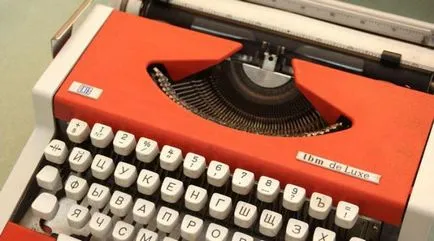
В пишещи машини използват т.нар едноразряден шрифт, който се характеризира с еднакви символи широки. Смята се, че тя е по-неразбираем от един пропорционален на шрифта, който се използва в съвременната печат. Но днес тя се намира в програмирането, когато пишете код, този шрифт за писане на сценарии. Между другото, регистрационни номера, също са написани на Непропорционални шрифтове.
За да спестите място и намаляване на размера на устройството е често отделят много от ключовете. Така например, номера заменени heteronymous букви, тирета и тирета, са същите като цитати.
използването на
По-голямата част на ХХ век, всички официални държавни документи са написани на пишеща машина, издателят се изисква също да донесе отпечатания текст, тъй като това значително улеснява работата на Наборчици.
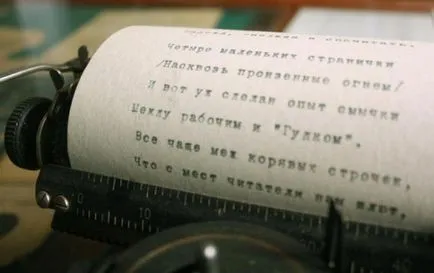
В средата на ХХ век, с появата на персоналните компютри, пишещи машини няма. Но пишеща машина шрифта е все още активно се използва от дизайнерите. Тя изглежда страхотно в много стилове, дава реколта ефекти. Впечатлението на работата на човека, а не прави бездушна машина.
Какво е името на пишеща машина на шрифта?
В момента има повече от 15 разновидности на тях за Photoshop. Всеки шрифт пишеща машина за "Photoshop" или имитира стила на конкретно устройство или пише в различни публикации (вестници, печат). Много стилове са на разположение и в двете на кирилица и латиница. Най-подобен шрифт изглежда B52 с голямо разстояние между знаците и ефекта на триене. Има и други шрифтове, например:
- DS Moster има доста интересен ефект, когато някои печатни са символи, които по-дебели. И писмата не са подредени точно в съответствие и "танц" прави текста много реалистичен.
- Underwood напълно копира стила на писане на едно и също име на машината.
- Хартинг и 1942. Доклад изглежда много износени, сякаш боята в машината започва да се изчерпи.
- Junkos пишещи машини силно стилизирани буквите в нея с различни размери и материал, много "мастилени петна".
- Пишеща машина, Тип наред и крал по-голям по-близо до компютъра или наборен, те са ясни, гладка и без малки петна.
- Стари вестници е подобно на стила на печат във вестници в началото на ХХ век.